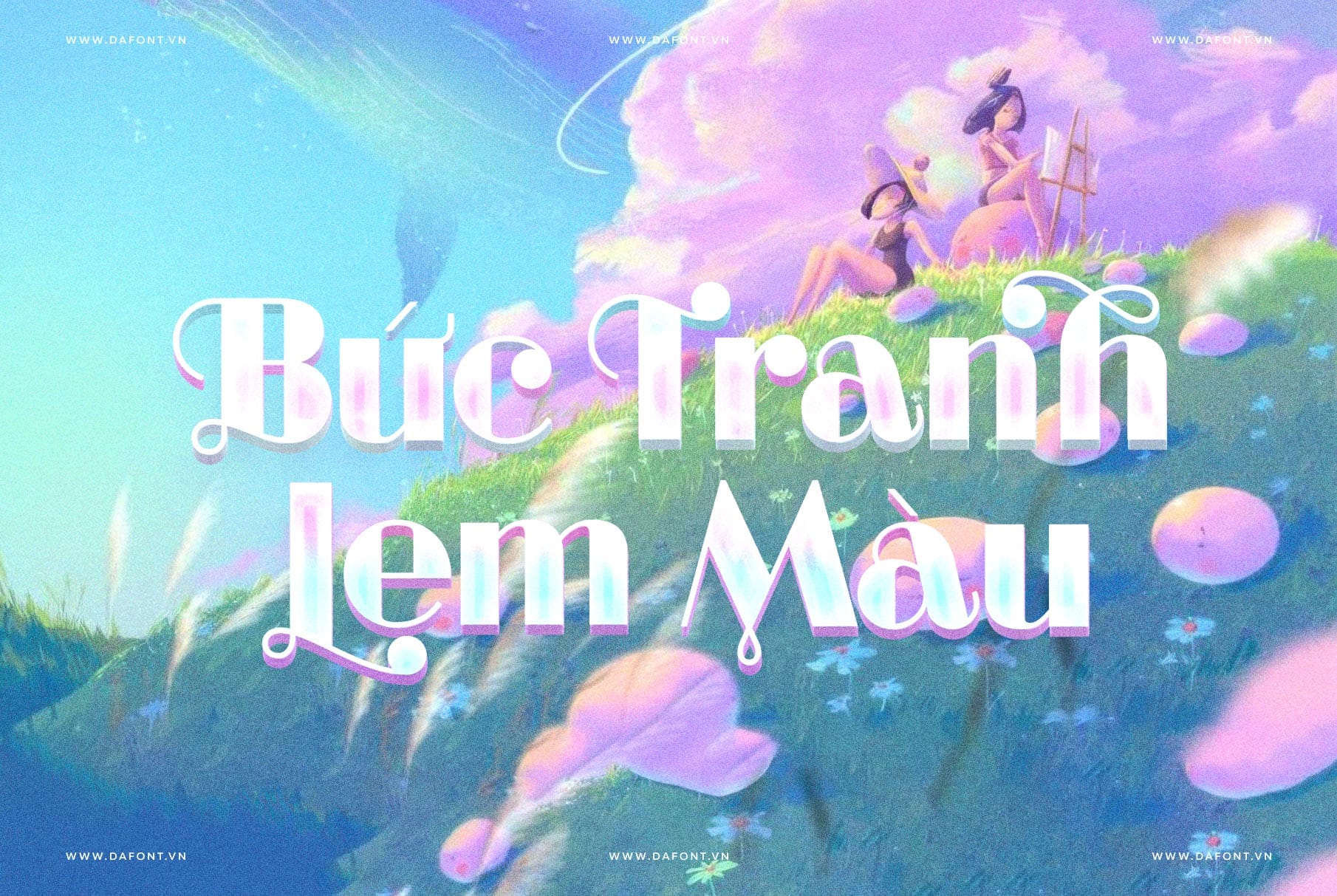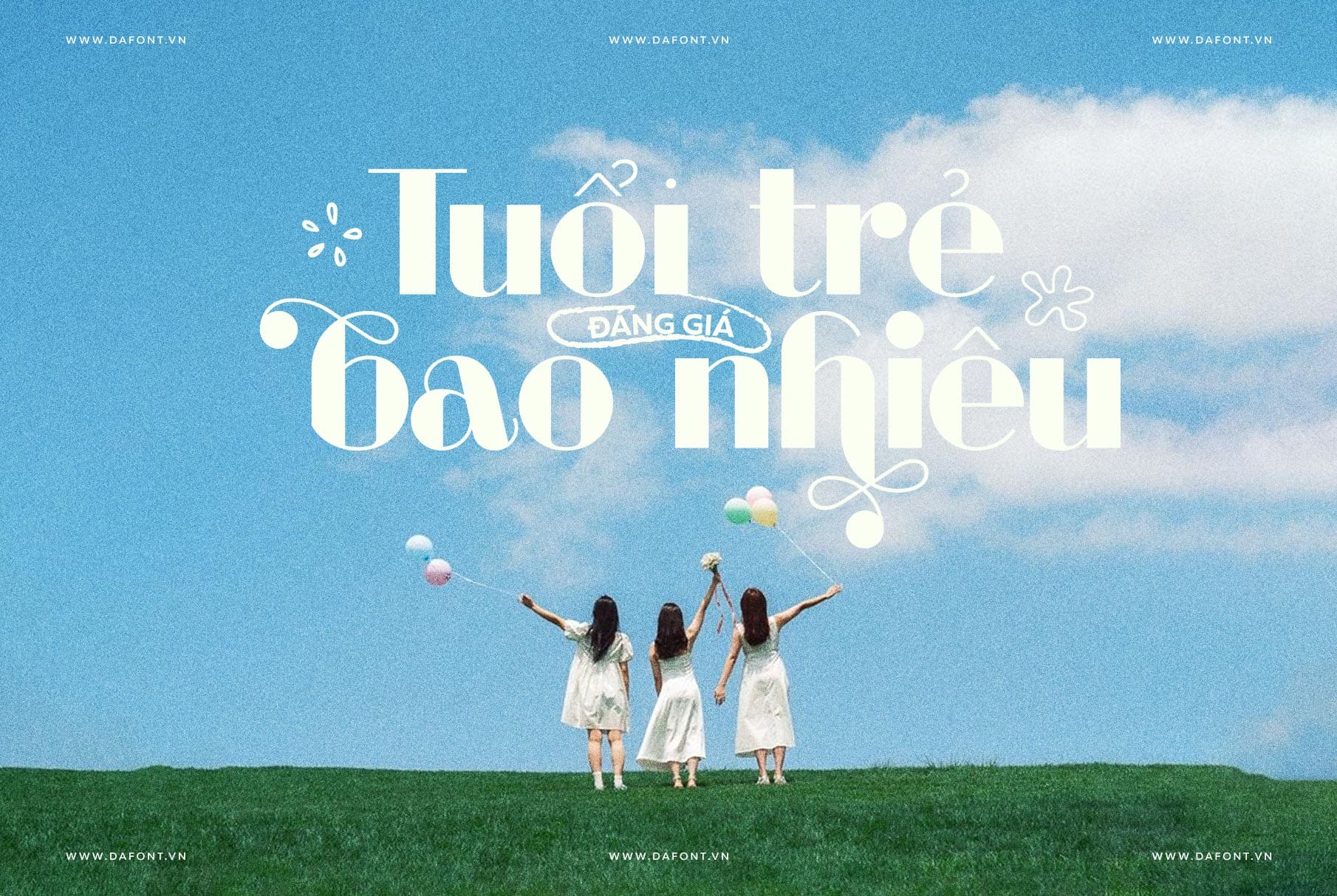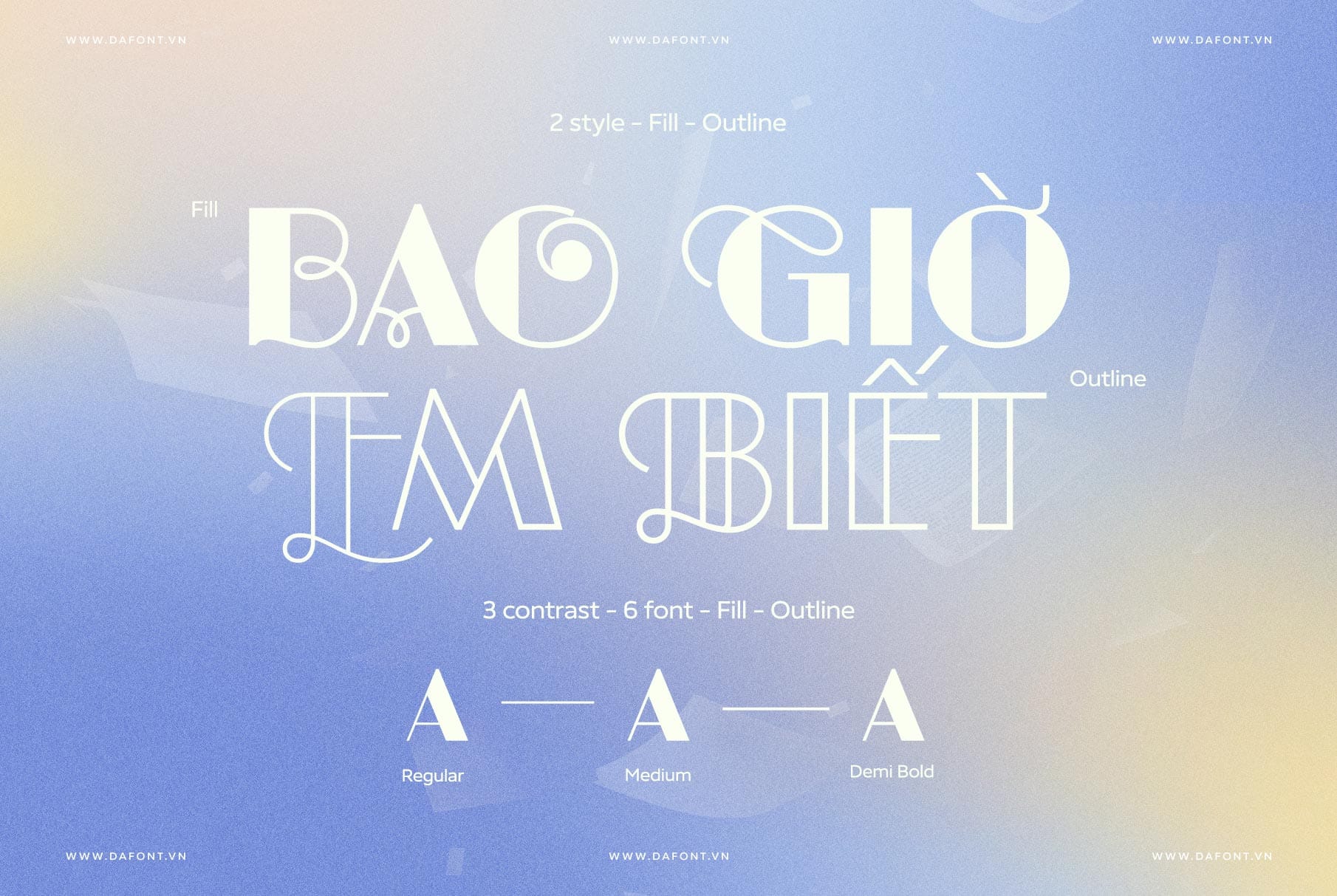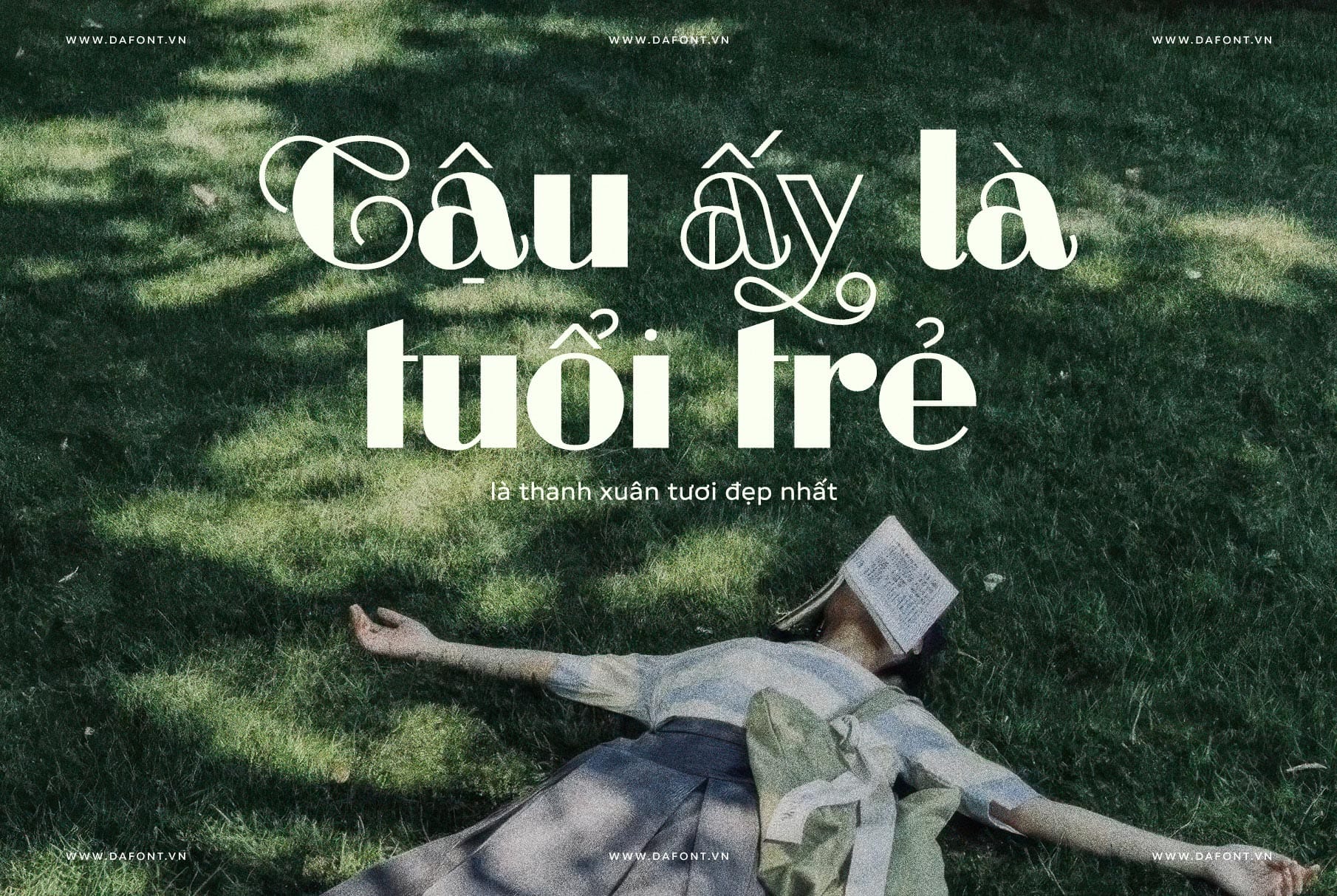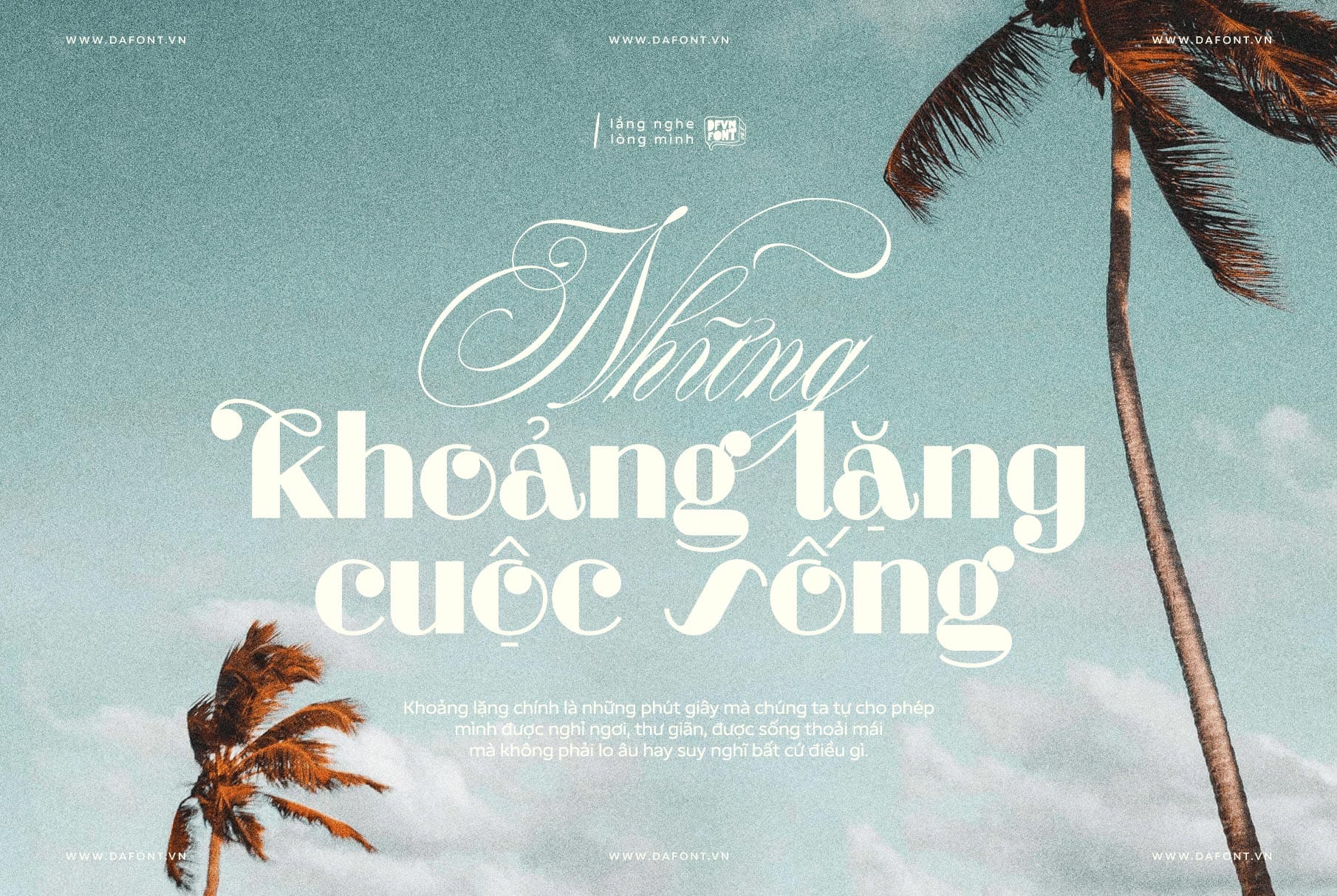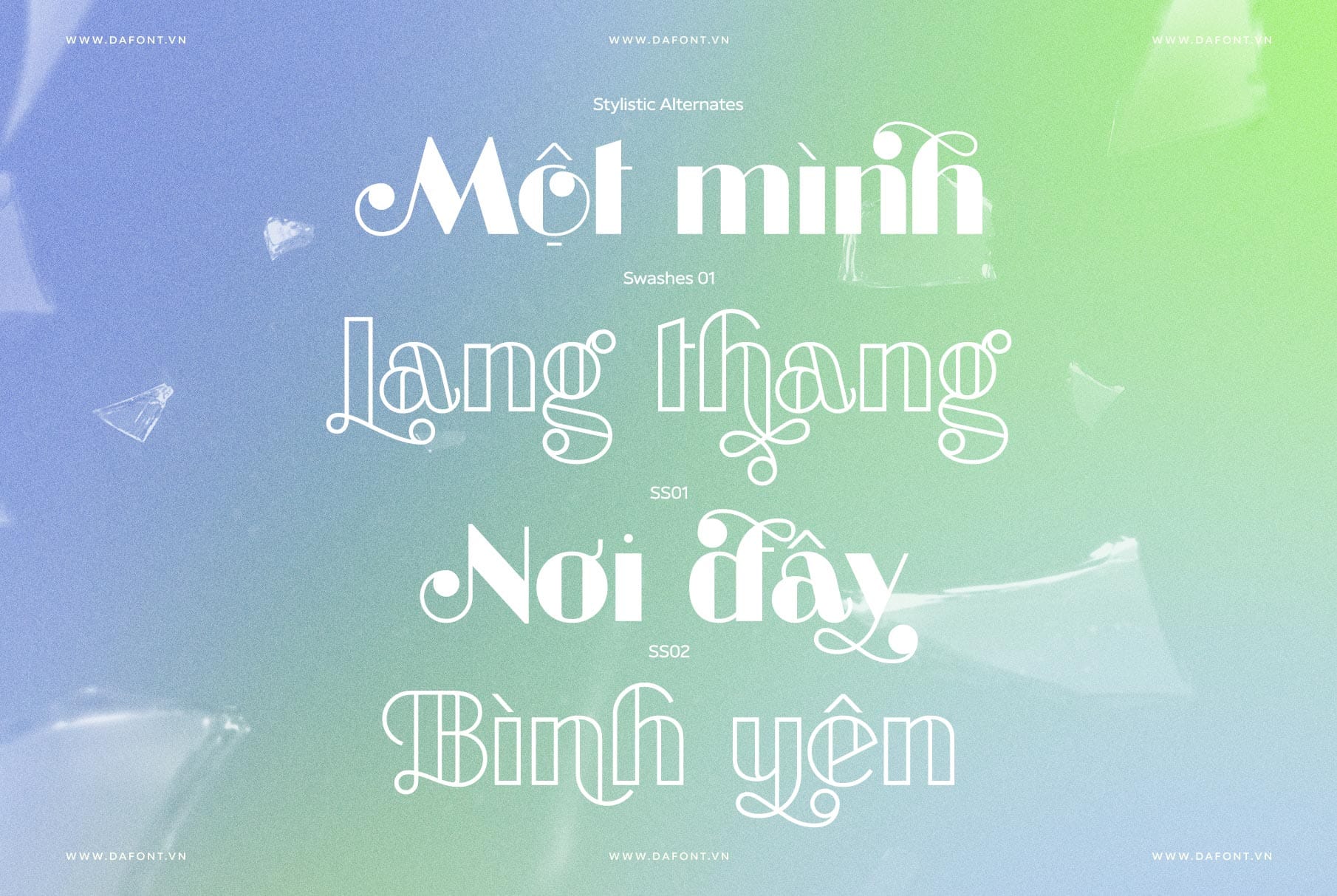
DFVN Bethari
Sự kết hợp hoàn hảo giữa thẩm mỹ và tính ứng dụng
DFVN Bethari là một font chữ display độc đáo nổi bật với phong cách Deco, kết hợp các đường nét swashes tinh tế, mang lại vẻ ngoài thanh lịch và ấn tượng. Với thiết kế hiện đại và khả năng ứng dụng linh hoạt, Bethari là lựa chọn lý tưởng cho các nhà thiết kế muốn tạo ra các sản phẩm vừa chuyên nghiệp vừa nghệ thuật.
Đặc điểm và Ứng dụng
DFVN Bethari có hai phiên bản chính: Fill và Outline, cùng với ba lựa chọn optical contrast (độ tương phản quang học), giúp người dùng linh hoạt trong việc áp dụng vào các dự án khác nhau. Font này nổi bật với các đường nét bold, tương phản cao và đường cong mượt mà, rất phù hợp cho:
• Thiết kế logo, danh thiếp và tài liệu nhận diện thương hiệu.
• Tạo tiêu đề, poster và các tài liệu quảng cáo cần phong cách ấn tượng.
• Sử dụng trong xuất bản kỹ thuật số như blog, tạp chí điện tử và sách điện tử.
• Ứng dụng trong giao diện người dùng (UI/UX) để đảm bảo trải nghiệm rõ ràng và tinh tế.
Lời khuyên: Sử dụng DFVN Bethari Việt hóa cho các ấn phẩm cần gây ấn tượng mạnh mẽ ở tiêu đề, logo hay poster cao cấp để tận dụng tối đa các biến thể và swashes trang trí của bộ font.
Kết luận
DFVN Bethari font là lựa chọn lý tưởng cho những ai cần một font display vừa “chất” vừa linh hoạt. Với hai phiên bản và ba mức tương phản, bạn có thể thỏa sức sáng tạo, từ tiêu đề website, logo đến ấn phẩm in ấn. Hãy trải nghiệm và biến ý tưởng thành hiện thực ngay hôm nay!
Bộ font được Việt hóa đầy đủ, các dấu được căn chỉnh hài hòa, kerning tòa bộ ký tự bao gồm cả các ký tự thay thế. Đặc biệt, với hơn 1.000 ký tự thay thế được thêm vào và dễ dàng sử dụng bằng tính năng Opentype.